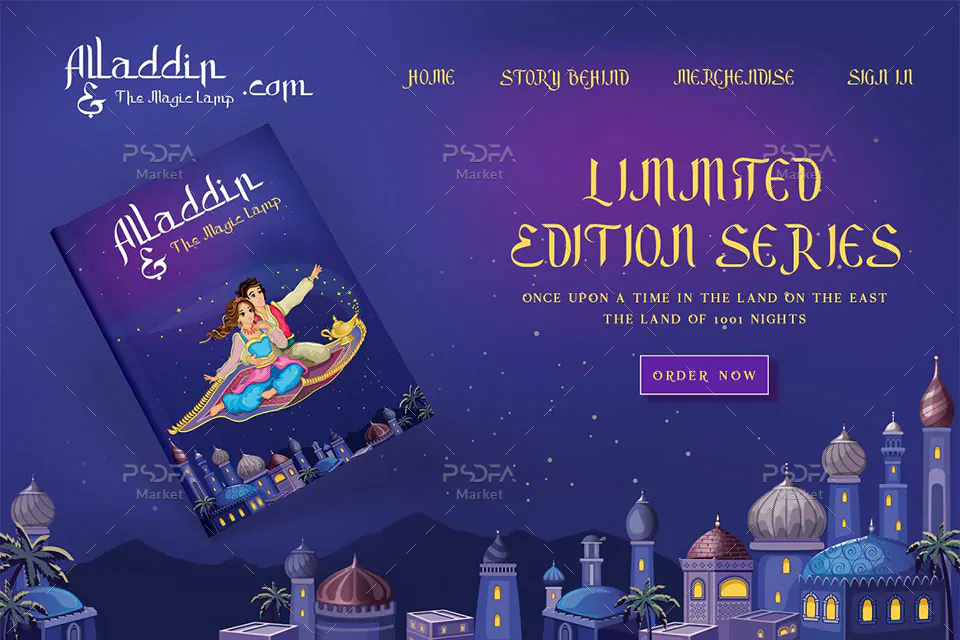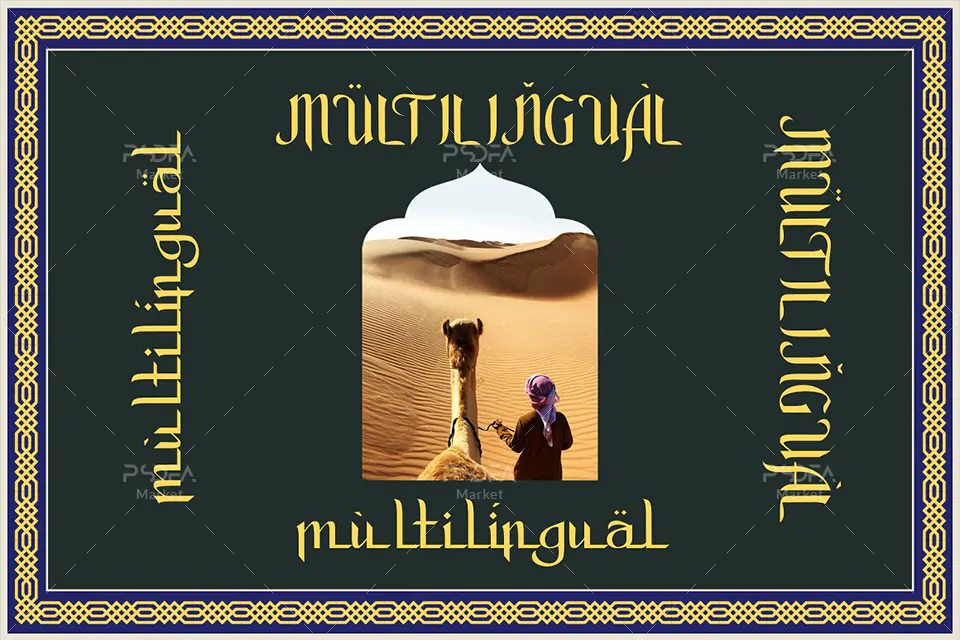
فونت انگلیسی به سبک و استایل عربی Zahra یک قلم فوق العاده زیبا با کاراکترهای متنوع است که میتوان از آن در طرح و پروژههای گرافیکی مختلف استفاده نمود. فونت Zahra با فرمتهای otf, ttf, woff, woff2 در فایل محصول قرار دارد که میتوان در نرم افزارهای مختلف از این فونت استفاده نمود.
فونت Zahra با وزن معمولی طراحی شده است که میتوان از آن در طراحی انواع کارت تبریک، پوستر، تراکت، بنر، بسته بندی محصولات، لوازم التحریر، طراحی صفحات وب و … استفاده نمود. برای استفاده از تمامی کاراکترهای این فونت باید از گزینه Glyphs نرم افزار فتوشاپ استفاده نمائید.